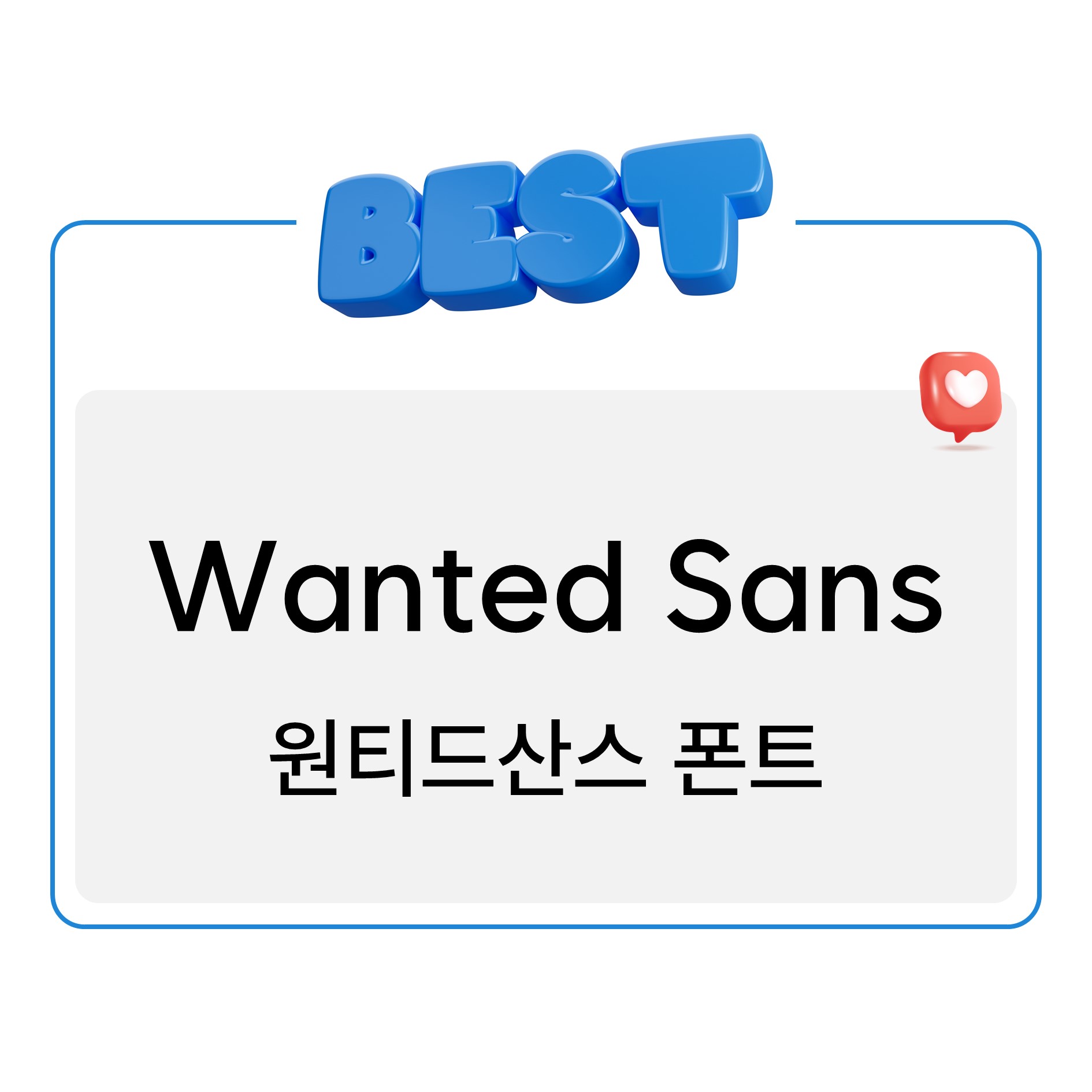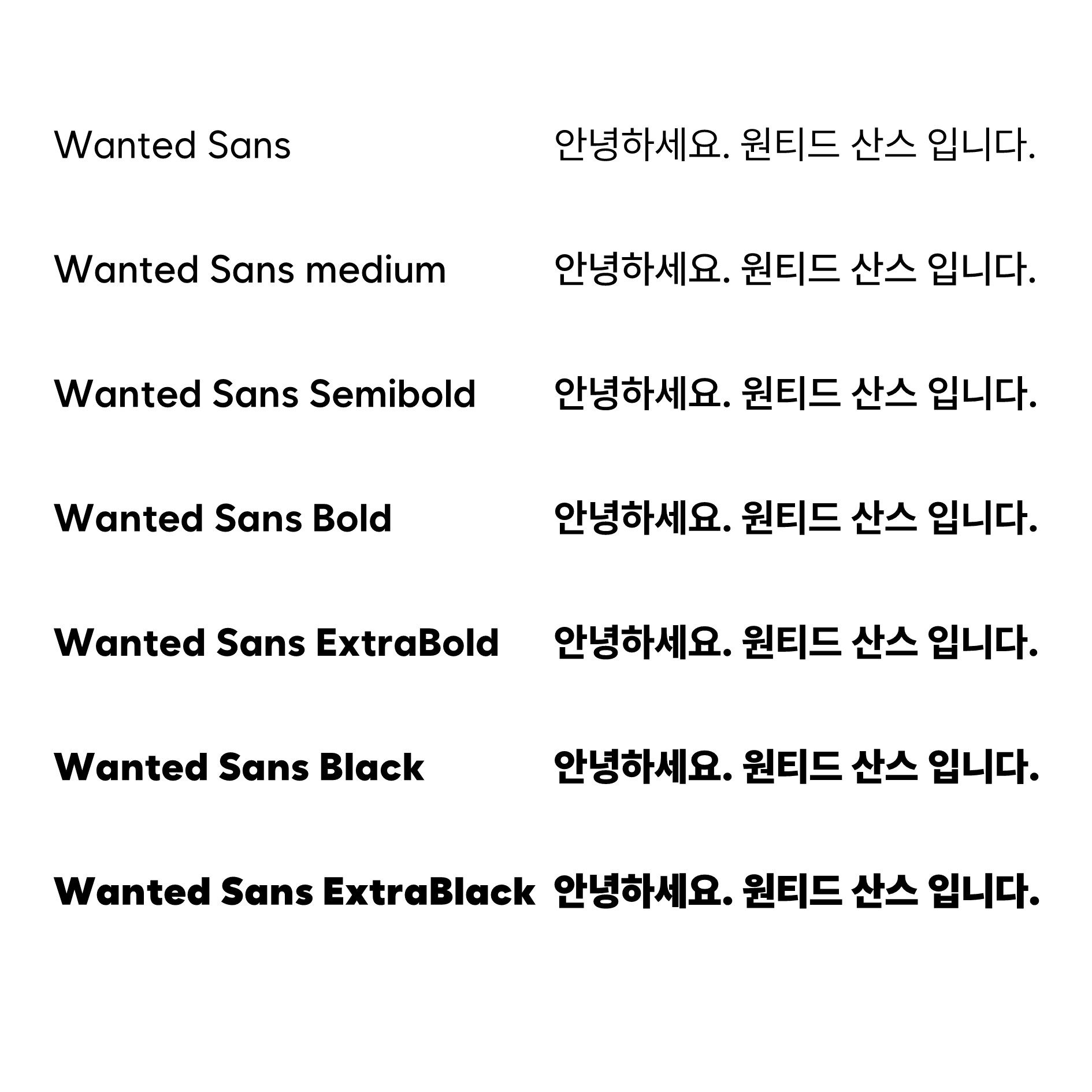
원티드산스 폰트
디자인 여러 방면에서 사용성이 높은 폰트가 나와서 추천드려요.
원티드랩(Wanted Lab)에서 나온 Wanted Sans 원티드산스 폰트 입니다.
원티드랩에서 원티드산스를 만들게 된 스토리가 브런치에 올라왔는데 정말 흥미로운 부분이 있었습니다.
원티드산스 폰트가 스포카 한 산스 폰트의 제작자와 프리텐다스 폰트 개발자가 함께 제작한 폰트라는 것이였죠.
벌써부터 완성도 높을 것으로 예상되는 폰트이지 않나요?
원티드산스 폰트는 총 7개의 굵기로 이루어져 사용성이 높습니다.
언뜻 보았을 때는 프리텐다드와 무척 비슷해보이는 면이 있네요.
디자인 업계의 사람으로서 해당 폰트를 정말 유용하게 사용할 것 같아요!